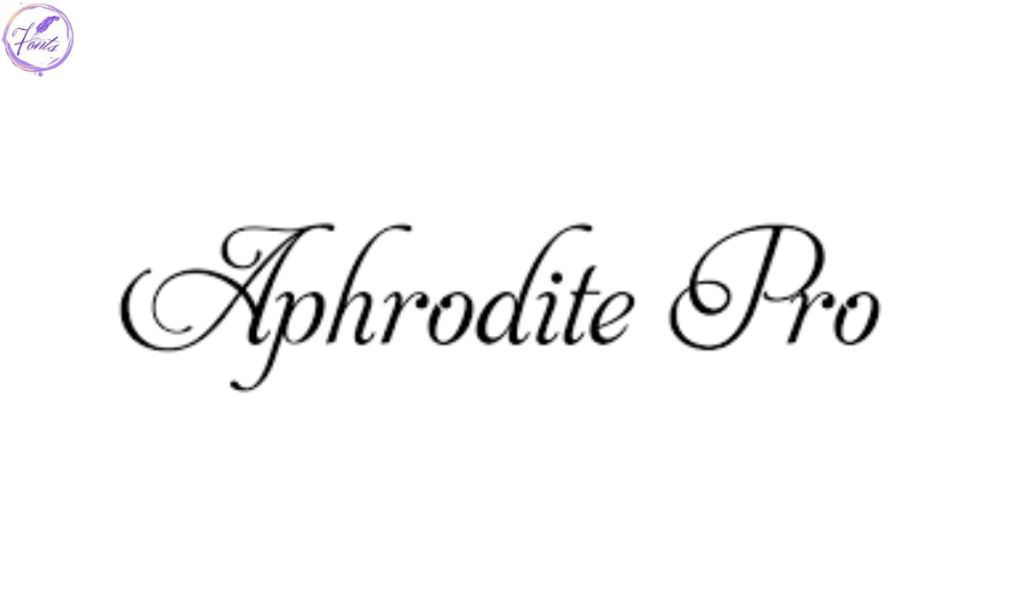
Font Aphrodite Pro việt hóa
Tác giả: Sabrina M. Lopez, Maximiliano R. Sproviero
Ngày phát hành: 2009
Phân loại: Cá tính, độc đáo
Kiểu chữ: Kiểu chữ viết tay
Font aphrodite pro là một trong những font chữ đẹp và sang trọng nhất hiện nay. Được thiết kế bởi tác giả nổi tiếng Sabrina M. Lopez, Maximiliano R. Sproviero vào năm 2009, font này nhanh chóng trở thành lựa chọn yêu thích của nhiều nhà thiết kế đồ họa. Với những đường nét uốn lượn, tinh tế và duyên dáng, font aphrodite pro mang đến sự quyến rũ và phong cách độc đáo cho bất kỳ dự án thiết kế nào. Font này đặc biệt phù hợp cho các thiết kế thiệp cưới, logo, tiêu đề và các dự án đòi hỏi tính nghệ thuật cao.
Đánh giá font aphrodite pro
Font aphrodite pro được đánh giá cao không chỉ bởi vẻ đẹp mà còn bởi tính ứng dụng linh hoạt của nó. Người dùng yêu thích font này vì nó mang lại cảm giác mềm mại, lãng mạn và rất dễ đọc. Với sự hỗ trợ đa ngôn ngữ, bao gồm cả tiếng Việt, font aphrodite pro giúp các nhà thiết kế dễ dàng tạo ra các tác phẩm mang đậm dấu ấn cá nhân. Ngoài ra, tính năng ligature và alternative characters của font này cũng giúp tạo nên những văn bản độc đáo và ấn tượng hơn.